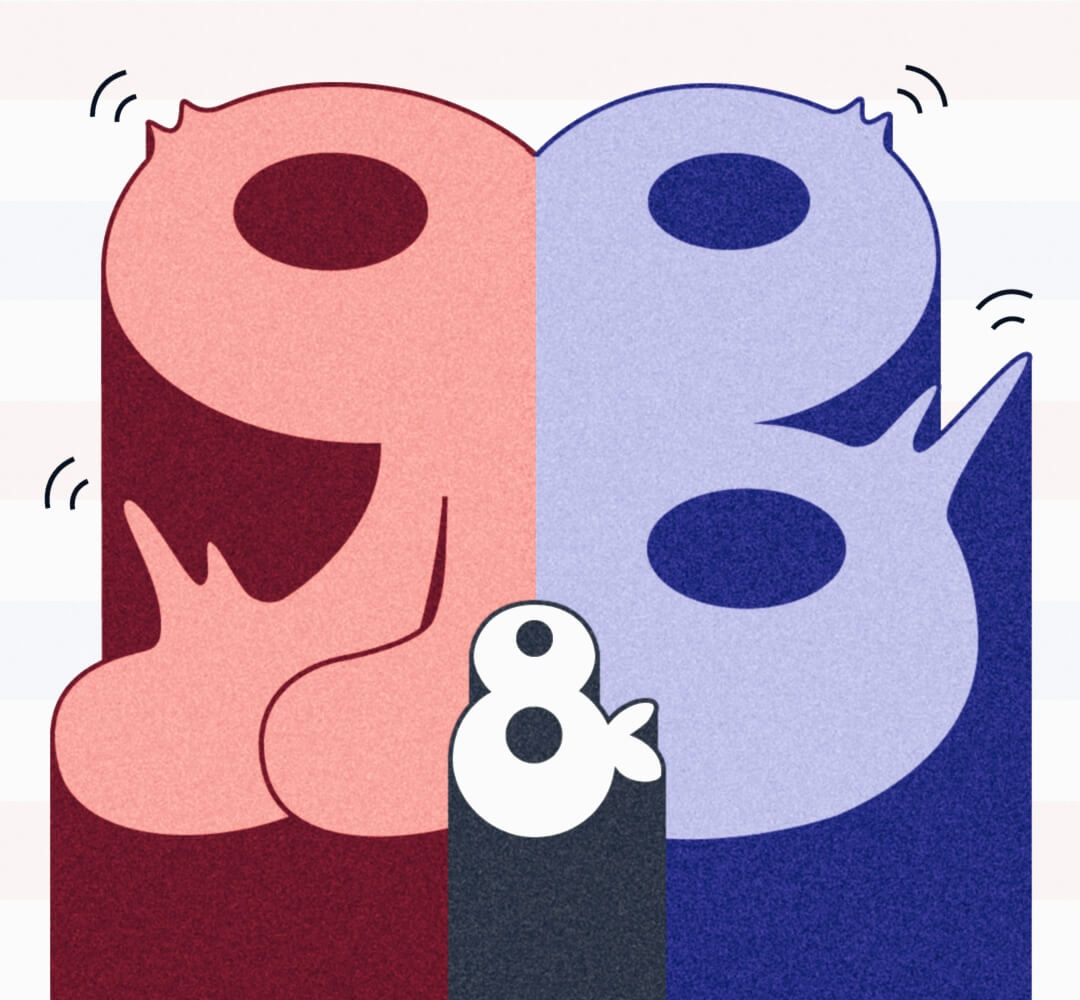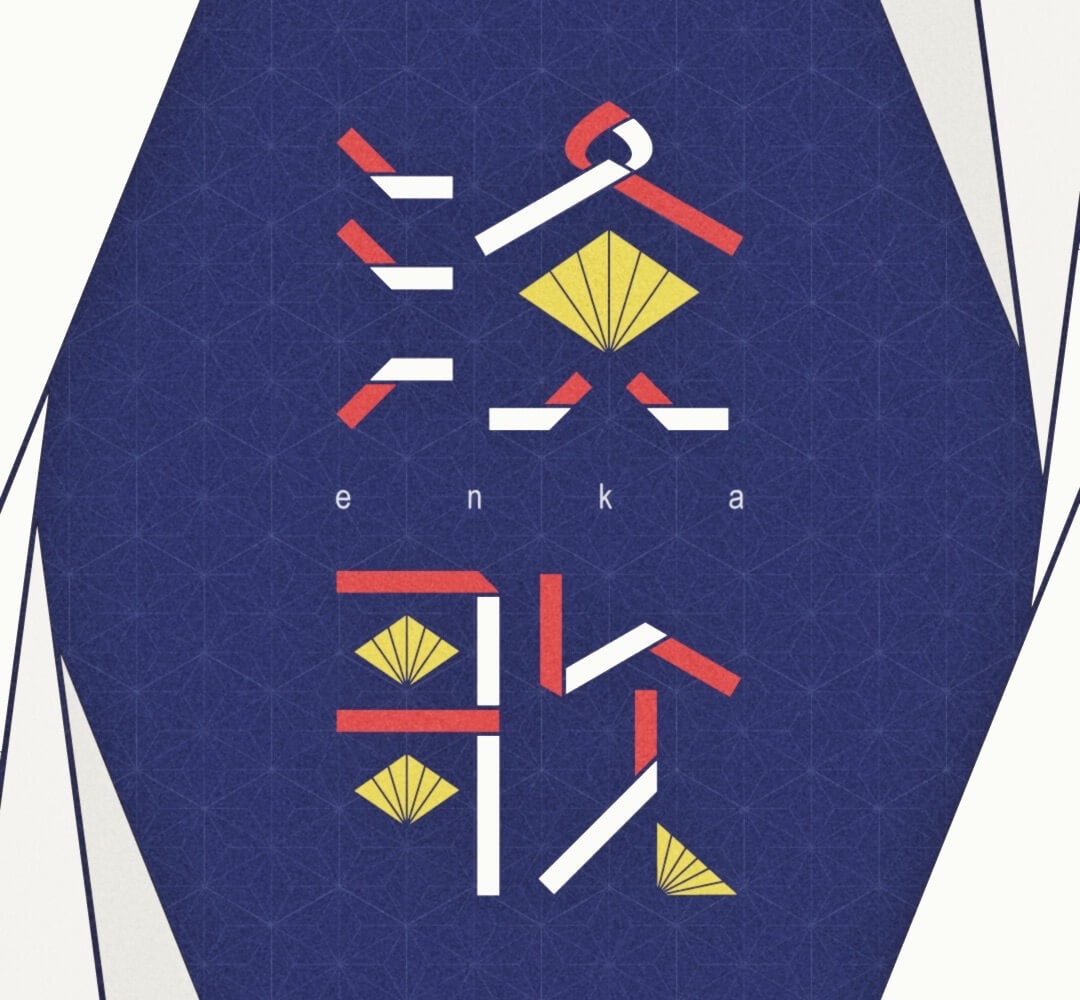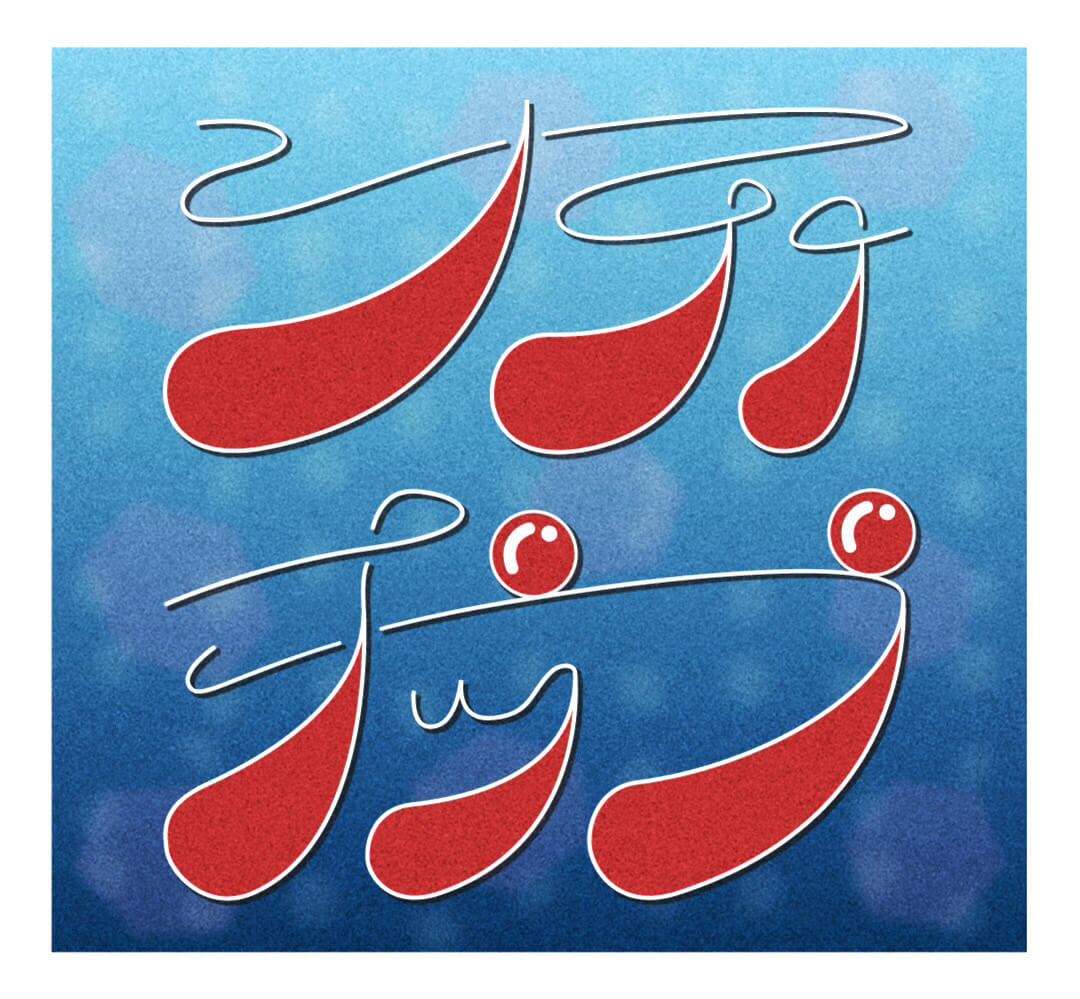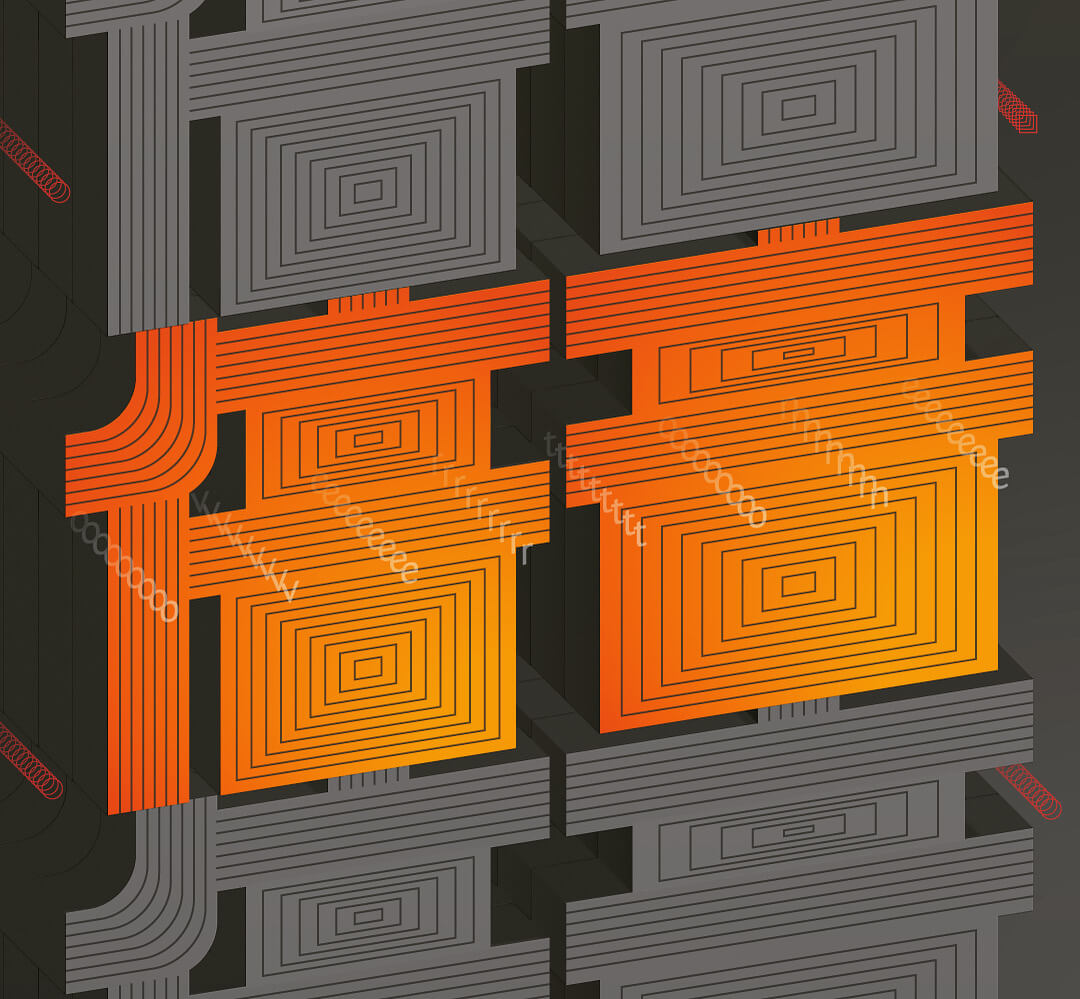
29歳 女性 会社員
▼ストーリー
今日から1週間、旦那が出張することになった。久しぶりにできた1人の時間。2人の時間も勿論好きだけど、せっかくだしこの1週間は全力で1人時間を楽しんでみよう。
とは言ってもお金に余裕があるわけでもないから…豪遊とまではいかない贅沢…となると、映画を見ながら、ちょっとリッチなお酒でも飲んでみる、というのはどうだろう。
音楽用語を題材にした自作タイポグラフィ(「倍音」と書いてございます)
▶「倍音」とは、ある周波数を基準とした「◯倍の周波数を持つ音」のことを言います。そのため、文字や線形が幾重にも重なるようにデザインを施しています。
▶︎幾つも文字がありつつも、無彩色+オレンジの配色とすることで、中央の文字に自然に視線がフォーカスされるように工夫しました。
音楽用語を題材にした自作タイポグラフィ(「答えは風に吹かれている」と書いてございます)
▶ボブ・ディランさんの楽曲で歌われている歌詞の有名な和訳です。「誰にも未来はわからない」といった意味合いですが、そこを肯定的に捉え、「予測不能な未来を楽しんでいきたいな」という思いで、楽しげな作字に仕上げました。
▶「グリーンの混じる水面に、善い知らせを想起させる黄金の風が凪いでいる」というシーンをイメージしてデザインしています。